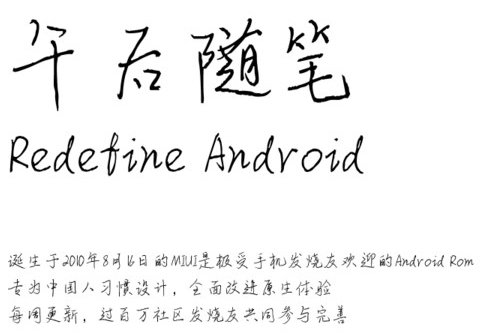
午后隨筆字體是漢儀字庫推出的一款閑雅慵懶的手寫字體,讓大家感受午后的的寧靜和放松,讓你的文字更有味道,綠色資源網(wǎng)誠意推薦!
一杯咖啡、一頁紙、一支筆、一縷陽光,一個(gè)屬于自己的午后時(shí)光……
午后隨筆體字跡清晰而沉穩(wěn),如時(shí)光般的透徹與可貴,給人一份慵懶而認(rèn)真的生活態(tài)度體驗(yàn),讓文字擁有自己的靈魂,可以適用在藝術(shù)設(shè)計(jì)、文化排版、包裝策劃等場合當(dāng)中。